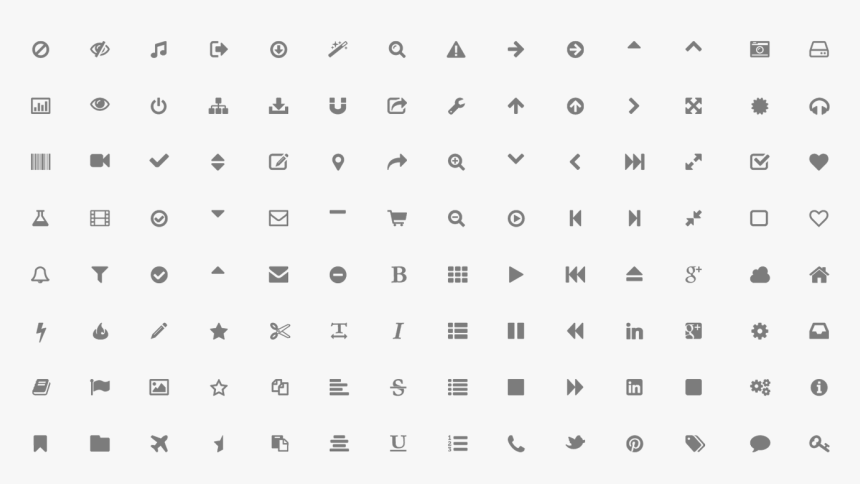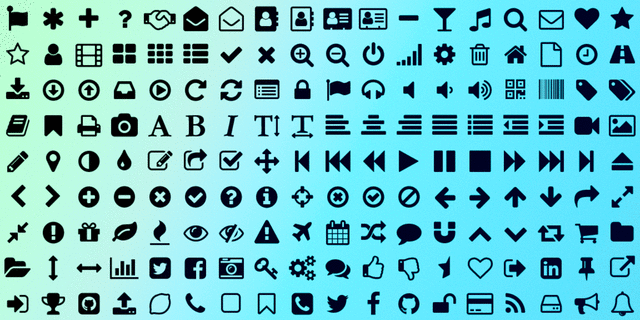
Download font awesome – bộ icon font phổ biến nhất thế giới với hơn 10,000 icon miễn phí, được sử dụng rộng rãi trong thiết kế bao bì sản phẩm, túi giấy, catalogue và in ấn thương mại. Font Awesome cung cấp icon cho mọi nhu cầu từ social media, contact, feature đến icon hướng dẫn sử dụng sản phẩm.
Font Awesome là gì?
Font Awesome là bộ icon font được phát triển bởi Dave Gandy và ra mắt lần đầu năm 2012. Khác với font chữ thông thường, Font Awesome là icon font – mỗi ký tự trong font tương ứng với một icon đồ họa. Điều này cho phép designer dễ dàng sử dụng hàng nghìn icon chỉ bằng cách gõ phím hoặc copy mã code.
Font Awesome đã trở thành tiêu chuẩn công nghiệp cho icon trên web và cũng được sử dụng rộng rãi trong thiết kế in ấn nhờ chất lượng icon sắc nét, đa dạng và dễ sử dụng. Hiện tại Font Awesome đang ở version 7, với hơn 10,000 icon trong phiên bản Pro và khoảng 2,000 icon trong phiên bản Free.
Các phiên bản Font Awesome:
- Font Awesome 4.7.0: Phiên bản legacy cuối cùng của dòng 4.x, vẫn được nhiều người sử dụng do tính tương thích.
- Font Awesome 5: Phiên bản lớn với nhiều cải tiến, phân chia thành nhiều style: Solid, Regular, Light, Brands.
- Font Awesome 6: Phiên bản hiện đại với thêm nhiều icon mới, cải thiện chất lượng.
- Font Awesome 7: Phiên bản mới nhất với icon đa dạng và nhiều style hơn.
Các style Font Awesome:
- Solid: Icon đặc, tô kín – phù hợp cho tiêu đề, điểm nhấn.
- Regular: Icon viền nét, không tô – phù hợp cho nội dung nhẹ nhàng.
- Light: Icon viền mảnh – thanh lịch, tinh tế (chỉ có trong Pro).
- Duotone: Icon hai màu – tạo chiều sâu (chỉ có trong Pro).
- Brands: Icon các thương hiệu: Facebook, Instagram, Twitter, Google…
Phân biệt Font Awesome Free vs Pro:
Sử dụng Font Awesome trong thiết kế in ấn
Font Awesome với hàng nghìn icon sẵn có giúp designer tiết kiệm thời gian và tạo tính nhất quán:
- Icon social media trên bao bì: Facebook, Instagram, YouTube, TikTok icon in trên túi giấy, hộp sản phẩm giúp khách hàng dễ dàng tìm thấy brand trên mạng xã hội.
- Icon contact information: Phone, email, website, location icon in trên catalogue, brochure, name card.
- Icon feature sản phẩm: Icon check, star, heart để highlight tính năng nổi bật trên bao bì.
- Icon hướng dẫn sử dụng: Icon mũi tên, warning, info để hướng dẫn người dùng trên nhãn sản phẩm.
- Icon menu nhà hàng: Icon coffee, pizza, burger, dessert để phân loại menu rõ ràng.
- Icon infographic: Icon chart, graph, người, nhà để tạo infographic sinh động trên catalogue.
Ưu điểm sử dụng Font Awesome cho in ấn:
- Sắc nét ở mọi kích thước: Vì là vector font, icon không bị vỡ hay nhòe khi phóng to/thu nhỏ.
- Dễ thay đổi màu sắc: Chỉ cần thay đổi màu chữ là icon đổi màu theo, không cần edit file riêng.
- Nhất quán style: Tất cả icon cùng style, tạo sự nhất quán cho thiết kế.
- Tiết kiệm thời gian: Không cần tìm hoặc vẽ icon từ đầu.
Ứng dụng icon Font Awesome trong bao bì
Icon Font Awesome xuất hiện rộng rãi trong nhiều sản phẩm in ấn:
- Bao bì sản phẩm: icon social media, icon feature, icon hướng dẫn trên hộp.
- Túi giấy thương hiệu: icon Facebook, Instagram, website ở mặt sau túi.